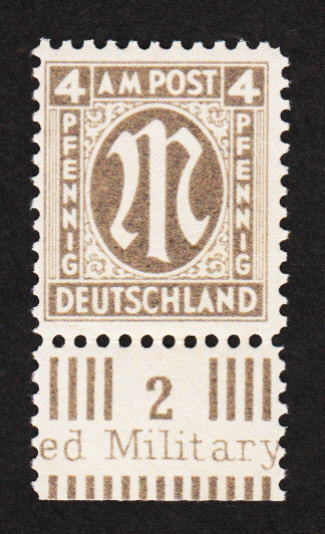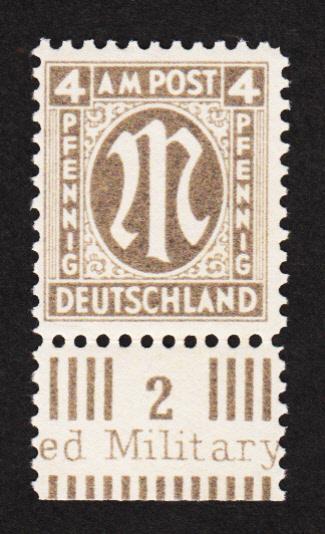
Wohl Fraktur, aber welche?
ich bin neu hier und suche die Schriftbezeichnung für nur einen einzigen Buchstaben! Es handelt sich um ein großes M, das auf den ersten Nachkriegsbriefmarken in der Mitte eines Ovals als Zeichen für "Military"  zu sehen ist. Angeblich soll es Old English sein, was ich aber nicht glaube. Der Entwurf der Marke ist 1944 in den USA entstanden. Kann jemand diesen Buchstaben einer bestimmten Schrift zuordnen? Die übrige Beschriftung der Marke ist Gothic.
Die Form des Buchstabens ist offenbar so gestaltet, dass sie ins Oval der Marke passt, und würde in einer normalen Schrift überhaupt nicht funktionieren. Das M ist also
ziemlich sicher indiviudell für die Marke gezeichnet
Andere Ideen wird es kaum geben. Normale Schriftarten können so ein M nicht haben – schon allein weil die drei Stämme dann auf einer einheitlichen Grundlinie stehen müssten. Dieses M wurde aber eindeutig in diese Ovalform eingezeichnet/geschrieben. Es ist also eindeutig ein Einzelentwurf.
Wie schon gesagt: Einer exakten Schriftart ist das M als Unikat nicht zuzuordnen, »andere Ideen« könnten sich also nur allgemein auf den Stil beziehen. Zu diesem könnte man noch anmerken, daß die Form ca. von Empire bis Jugendstil inspiriert ist, also eher zu Jahrhundertwende bis zu den Zwanzigern passen würde als zu 1944. Das war also bei Erscheinen schon eine »Retro«-Gestaltung.
Ich würde dieses M noch nicht einmal in richtung Jugendstil schieben, die Form ist eigentlichg viel älter.
Die genertelle Form dieses M entspricht viel mehr dem M einer Schwabacher, mit dieser Form, bestehend aus etwas, das aussiht wie eine 2 (oder das runde r) gefolgt von diesen senkrechten Stamm in der Mitte, der hier, damit das ins Oval passt nach oben und unten verlängert wurde und als drittes bein, die erste Form praktisch auf den Kopf gestellt. Das ist schon ein frei gezeichneter Entwurf, nur eben auf der Schwabacher basierend - sollte wohl schön "german" wirken.
Vielen Dank für den Hinweis auf Schwabacher. Ich finde das auch ganz passend als Ideengeber und aus der Sicht eines Amerikaners vielleicht wirklich deutsch wirkend.